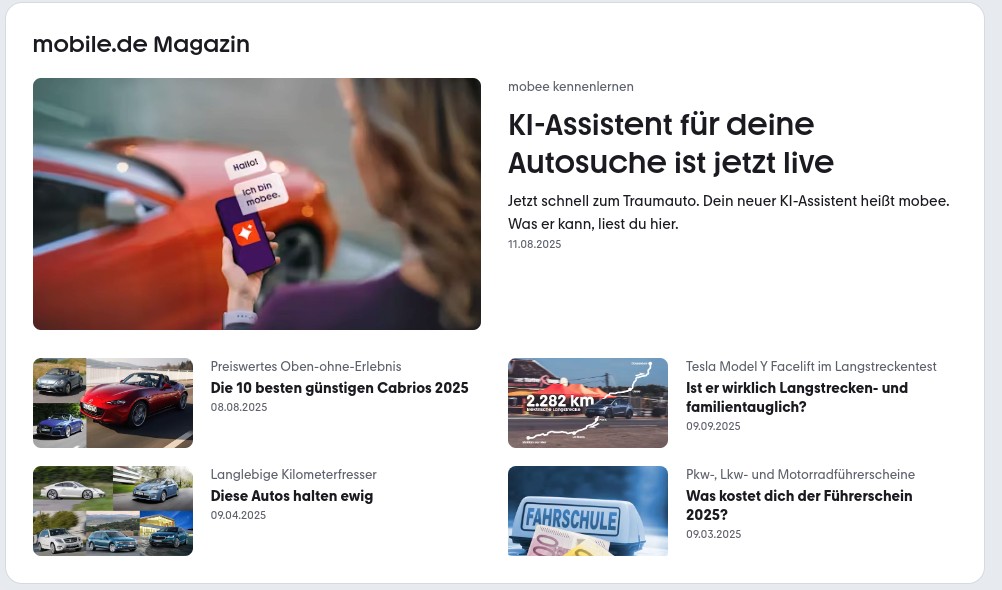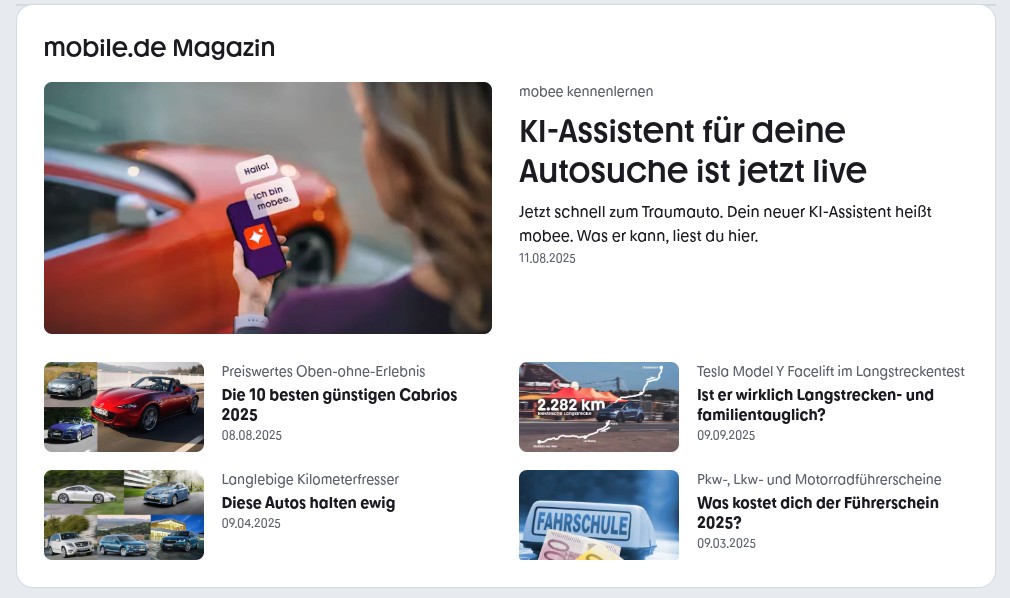
ich habe hier ein debian sid System mit zwei installierten Browsern: Falkon und MS Edge.
Seit ein paar Tagen habe ich folgendes Problem:
Surfe ich die Webseite „mobile.de“ an, werden nur unter Edge die angezeigten Zeichen auf verschiedener Unterlinie angezeigt (sie sind optisch wellenartig, je nach Buchstabe, mal mehr, mal weniger nach oben verschoben, während andere Buchstaben an der Unterlinie starten).
Dieses Problem ist neu und trat früher nicht mit Edge auf. Mit falkon tritt es gar nicht auf: da wird genau derselbe Webfont verwendet wie von Edge, aber dieses unschöne wellenartige ist dort nicht vorhanden.
Wie kann ich die Schriftdarstellung in Edge reparieren?
Es liegt NICHT am Font, da falkon diesen Font sauber darstellt.
Es liegt NICHT am Fallback-Font, da beide Browser den von mobile.de als Web-Font bereitgestellten Zeichensatz verwenden.
vielleicht magst Du mal einen Screen Shot machen und einstellen. Möglicherweise geht es noch anderen wie mir und können sich nicht vorstellen, was Du mit Deiner Beschreibung meinst.
Danke für die Bilder. Ich bin völlig baff. Sowas habe ich noch nie gesehen. Da scheint der Edge den Font wiederholbar völlig falsch zu rendern.
Ins Blaue geschossen, fielen mir nur so pauschale Hinweise ein wie „lösche mal den Cache von Edge“. Aber einen wirklichen Lösungsansatz kann ich nicht bieten.
Dir ist klar, was Sid ist? Das ist synonym für"experimentell". Da kann alles mögliche passieren, z.B. weil eine Anwendung und die von ihr verwendeten Bibliotheken nicht zusammen passen. Debian 13 wurde Anfang August releast. Das heisst, in Sid wird seitdem alles reingespült, was in den Monaten vor dem Release zurück gehalten wurde, mit allen Kompatibilitätsproblemen, die das mitbringt.
Ich nehme mal an, du nutzt Wine, um Edge laufen zu lassen. Da ist dieses Risiko in meinen Augen besonders hoch. Hinzu kommen noch die Unwägbarkeiten von Wine. Was in Version V funktioniert hat, funktioniert oft in Version V+1 nicht mehr.
Mein Rat: nimm wenigstens Testing. Da riskiert man in den Wochen und Monaten nach dem Releasewechsel auch das eine oder andere Problem, aber es hält sich in Grenzen. Ich halte mir in dieser Zeit immer noch eine Version des offiziellen Releases auf der Platte, damit ich nicht tagelang blockiert bin, weil z.B. Thunderbird nicht funktioniert.
Nein.
debian sid ist debian testing, nicht experimental. Ich habe auch gar keine Paket-Quelle aus experimental eingebunden.
Ich benutze nicht wine. Der Edge läuft hier native als reines Linux-Programm, kann sogar per apt-get updated werden.
debian sid läuft hier schon ziemlich lange ohne nennenswerte Probleme, auch wenn es „nur“ ein „testing“ ist. Außerdem kann ich sagen, dass ich solche Schriftprobleme zuvor nicht nicht beobachtet habe, also weder bei Edge noch bei einem anderen Browser.
Nein, Sid ist der Codename von „Unstable“ (nicht „Experimental“, da habe ich mich geirrt). Der Codename von Testing ist aktuell „Forky“. Was ist denn in /etc/apt konfiguriert?
Ok, das war mir nicht bekannt. Es ist aber kein Paket aus dem offiziellen Debian-Repository, das holst du dir von woanders, z.B. von packages.microsoft.com. Da ist das Risiko von Inkompatibilitäten aus meiner Sicht noch höher als bei Paketen aus dem offiziellen Unstable- oder Testing-Repository. Ich mache das mit QGis und das funktioniert oft wochenlang gar nicht oder mit Einschränkungen.
Ich wollte eigentlich nur darauf hinweisen, dass man bei Unstable/Sid immer mit solchen Effekten rechnen muss und bei Testing/Forky in den Wochen nach dem Releasewechsel auch. Meist werden solche Probleme innerhalb weniger Tage behoben. Ob das die Ursache für dein Problem ist, weiss ich nicht, aber es ist eine von vielen Möglichkeiten.
Wenn es den Edge als Flatpak-Paket gibt, dann würde ich das mal versuchen.
das klingt nach einem Rendering-Problem, das speziell mit der Rendering-Engine von MS Edge zu tun hat. Da Falkon den Font korrekt anzeigt, ist es wahrscheinlich, dass Edge die Schrift auf eine andere Weise rendert. Eine mögliche Ursache könnte das Anti-Aliasing in Edge sein. Manchmal verursacht das in Verbindung mit der Hardwarebeschleunigung merkwürdige Darstellungsfehler. Es könnte helfen, in den Edge-Einstellungen die Hardwarebeschleunigung zu deaktivieren oder die ClearType-Einstellungen in der Windows-Systemsteuerung zu überprüfen und anzupassen.
Da beide Browser denselben Webfont verwenden, liegt es nicht am Font selbst, sondern möglicherweise an der Art und Weise, wie Edge ihn rendert. Eine weitere Möglichkeit wäre, die font-smoothing -Eigenschaft in der CSS der Webseite zu optimieren, um das Rendering in Edge zu verbessern. Außerdem solltest du sicherstellen, dass Edge auf dem neuesten Stand ist. Wenn das Problem nach einem Update auftrat, könnte ein Downgrade oder das Zurücksetzen der Edge-Einstellungen helfen. Auch das Löschen des Caches könnte manchmal Wunder wirken.
Es könnte auch sein, dass es einen kleinen Unterschied in der Interpretation des Webfonts zwischen den beiden Browsern gibt, da Edge auf Chromium basiert und Falkon auf der QtWebEngine. In so einem Fall wäre es gut, das Problem an Microsoft zu melden, falls es ein Bug im Edge-Rendering gibt.
Schau auch mal in den Entwicklertools von Edge (F12), ob du Unterschiede in den berechneten Styles zwischen den beiden Browsern findest. Eventuell wird dort etwas anderes berechnet, was das Problem verursacht.